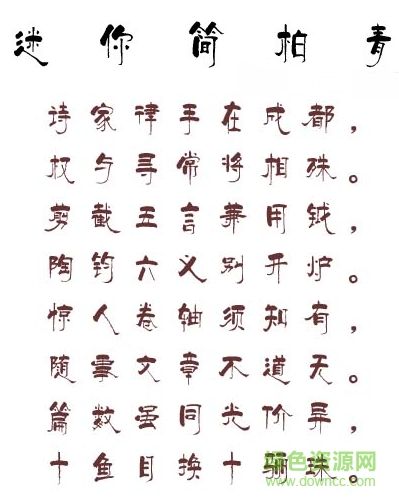
迷你簡柏青ttf是一款非常好用的迷你字體,支持中文簡體、英文以及阿拉伯數(shù)字,字體整體細長,非常的優(yōu)雅大方,歡迎喜愛此字體的用戶到綠色資源網(wǎng)下載使用!
該字體字體結構端正、重心平穩(wěn)、美觀實用、清晰醒目。適合應用于廣告設計、名片設計、包裝印刷、產(chǎn)品設計等應用。歡迎來綠色資源網(wǎng)下載。